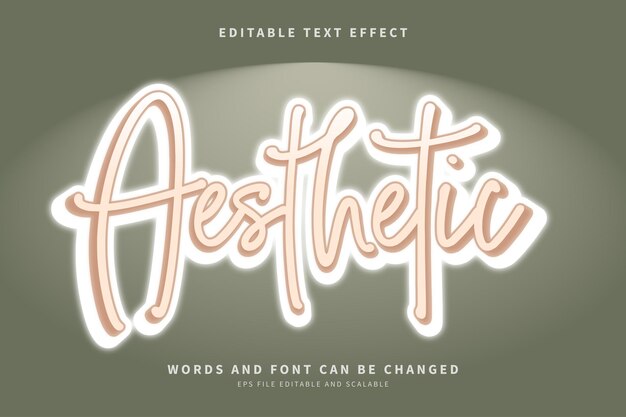
Редактируемый текстовый эффект, современное 3D-перо и минимальный стиль шрифтаРедактируемый текстовый эффект, современное 3D-перо и минимальный стиль шрифта
Редактируемый текстовый эффект, современное 3D-перо и минимальный стиль шрифта